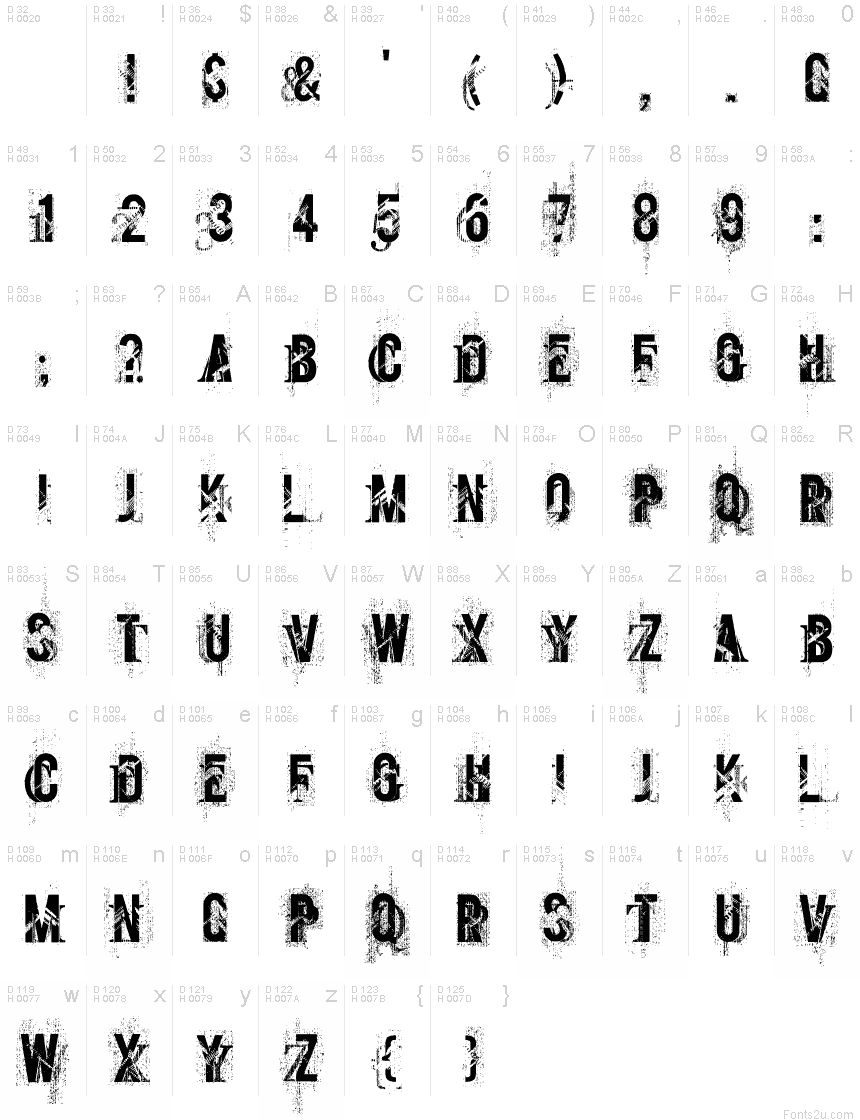
Screamo od Gyomsegs to darmowy, grunge’owy krój pisma typu display o wyrazistym, „zniszczonym” charakterze, rodem z punkowych ulotek i kserowanych grafik klubowych. Litery są ciężkie i teatralne, ale prawdziwym atutem jest ciągła fragmentacja form: plamki, głębokie rysy i surowe ubytki, które nadają alfabetowi zestresowany, rozmazany i nieco zadziorny wygląd.
Dzięki temu ten darmowy font naturalnie sprawdzi się na plakatach muzycznych, okładkach zinów, tytułach horrorów, grafikach streetwearowych i krótkich nagłówkach, gdzie zbyt czyste krawędzie wydawałyby się zbyt grzeczne. Wykorzystaj go, gdy chcesz, aby wielkie litery wprowadziły statykę i surowość – szczególnie w krótkich hasłach, logotypach czy tekstach na okładki, gdzie to właśnie zniszczona tekstura robi całą robotę.